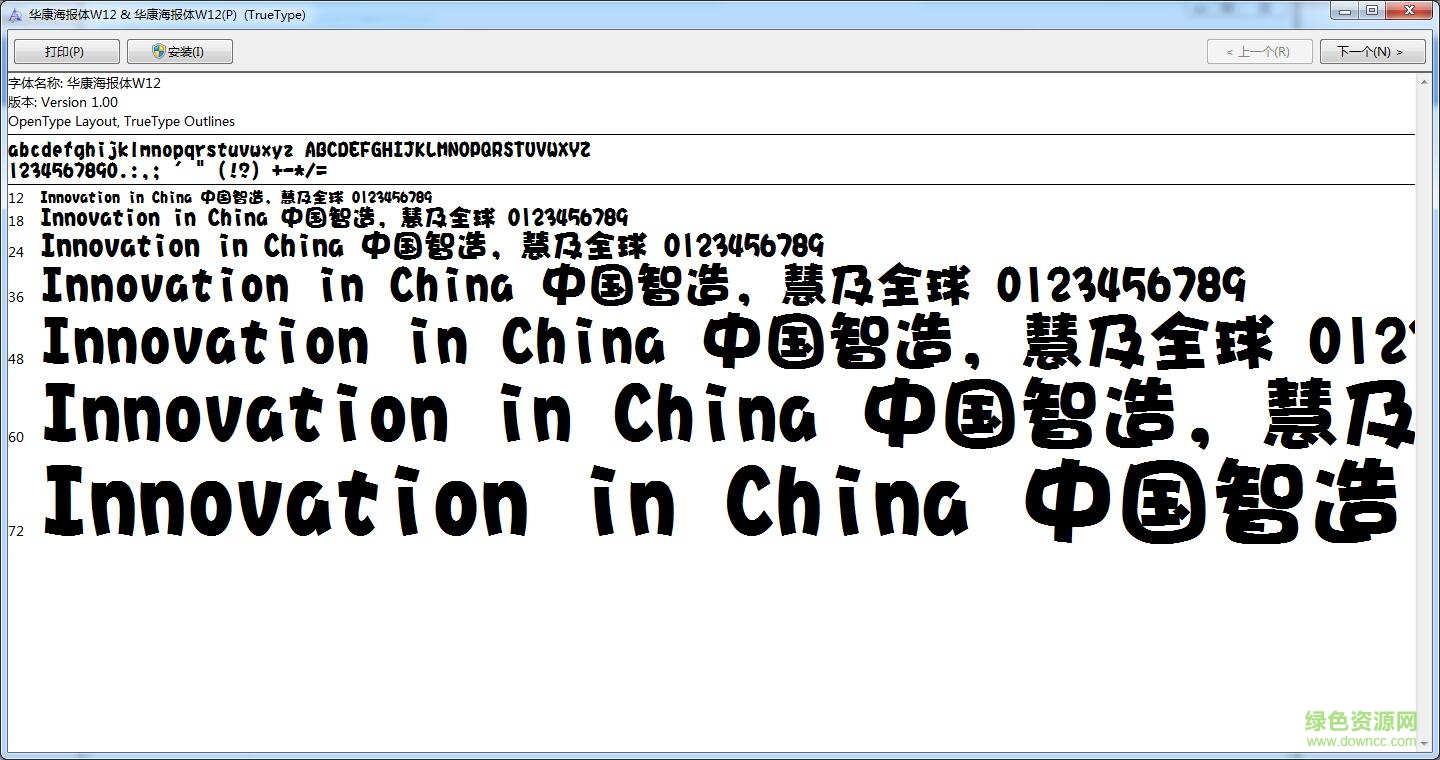
華康海報體w12p
華康海報體w12 p是一款免費字體應(yīng)用,這款字體看起來比較活潑,在進(jìn)行美術(shù)創(chuàng)作或者兒童類雜志編輯的時候,可以使用這款字體??靵砭G色資源網(wǎng)下載吧!
字體介紹
華康海報體W12可以為用戶提供英文字體和中文簡體字體,適合用于海報設(shè)計方面,字如其名!